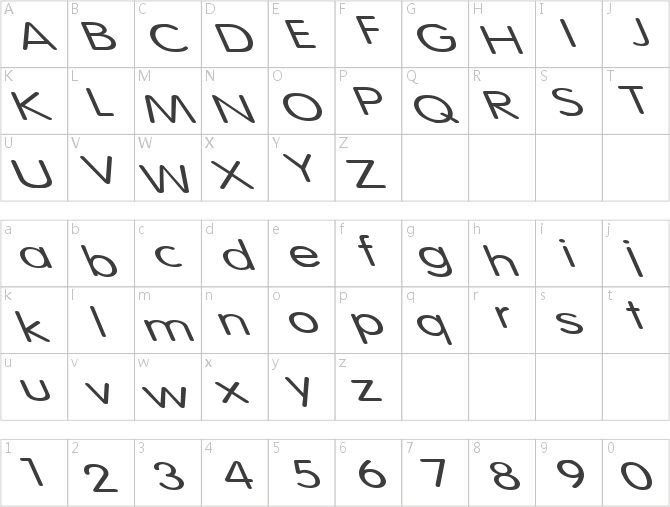
字体名称: Vogue-N
Vogue-Normal Ex Left
Vogue-Normal Ex Left介绍
Vogue-Normal Ex Left字体字库是一款让人赏心悦目、百看不厌的英文字体,适合各类广告和产品包装设计应用,字体大小0.1MB,格式为ttf字体,上传用户是woslxn,作者/版权方为未知